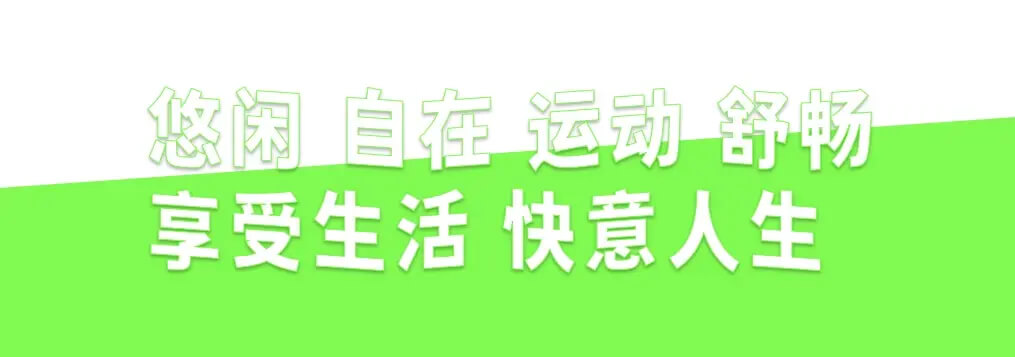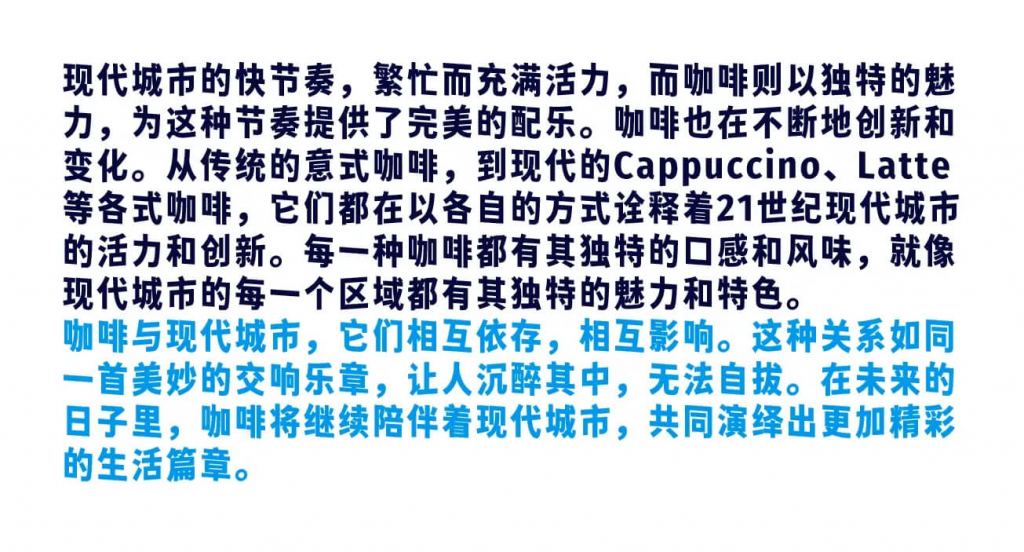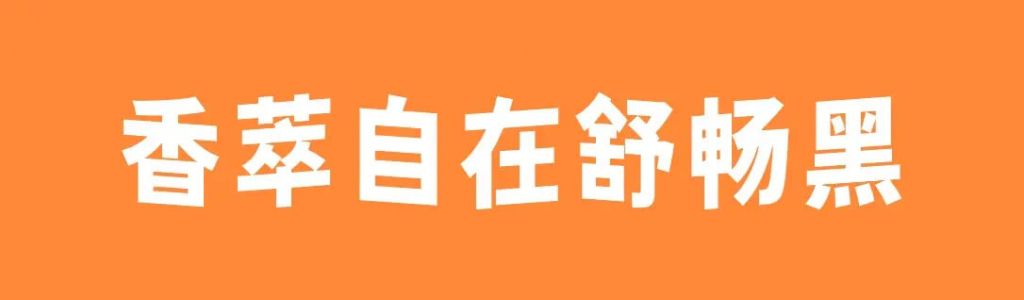
汉字作为方块字形的文字,非常适合构建波浪形,而传统楷书写法是纵向略偏长,因此汉字比西文字体更适合做这种改造。添加随机倾斜效果后的字体,宛如竖立的纸牌,具有立体感;而长段排版时,容易做出层次感。事实上,采用折笔更多、曲线更少、字面更大的字体,进行波浪化处理,能呈现更好的效果。但开源字体中,只有思源系列较适合做这类改造。由于现代汉语横向排版,所以没有选择横向随机倾斜,而是选择纵向倾斜,这同时也符合传统楷书的书写习惯,即“横画斜、竖画不斜”。
于是这款字体应运而生。“香萃自在舒畅黑”(Xiangcui Wave Sans)是一款基于开源字体“未来荧黑”,通过简单改造而形成的字体,支持简繁汉字。未来荧黑是由思源黑体改造而成,但更具简明、轻快的特征。未来荧黑剔除了思源黑体原有的喇叭口,和口字部件的竖脚,改变了重心,使其更富有现代化。香萃自在舒畅黑允许个人或企业免费商用。
字体呈长方形,多文本排列或长段正文使用时,会形成独特的波浪效果,极富趣味与动感、清新明快,适用于运动生活、等多种场景,可用于网络视听或各类日常商品的包装设计。
起这么长的字体名,是想在字体名称上更好突出波浪般的视觉效果。